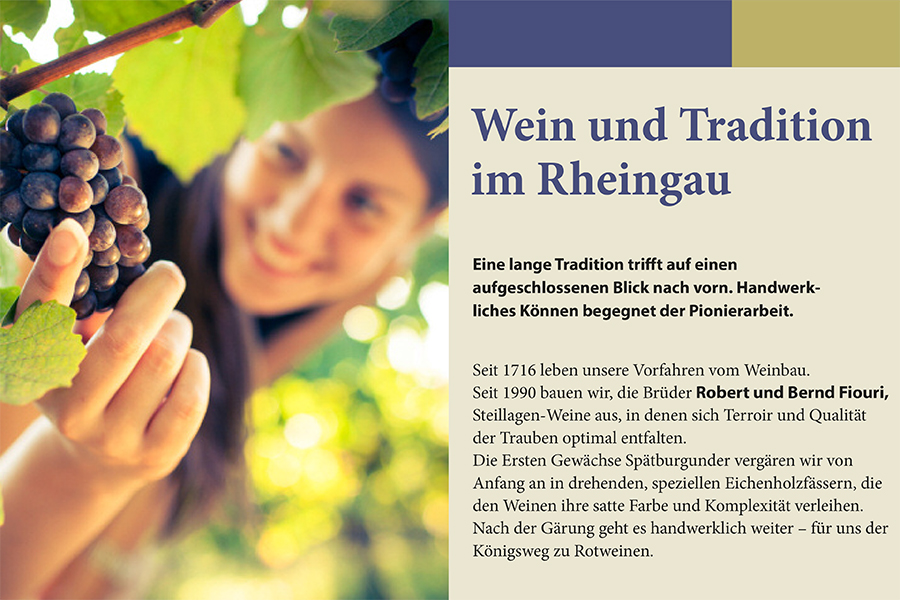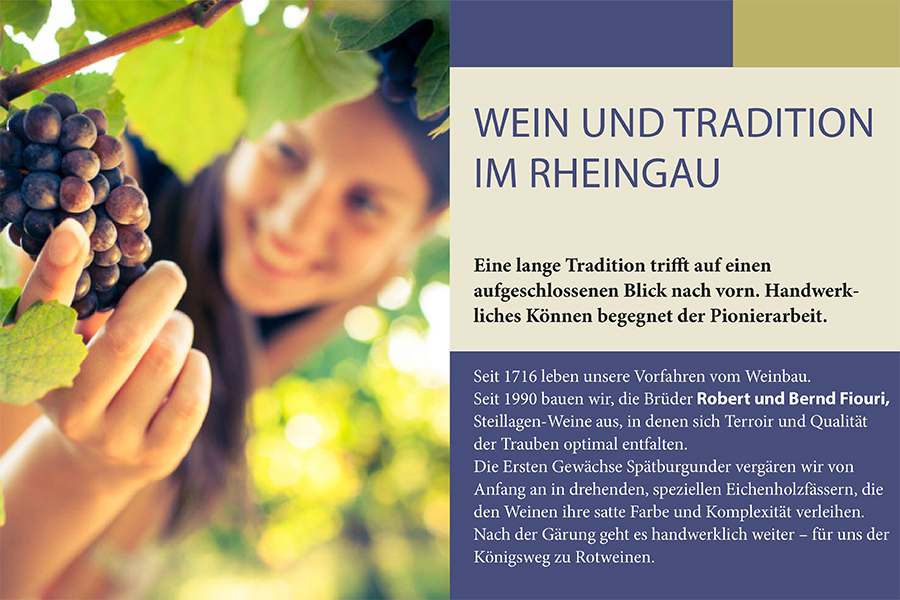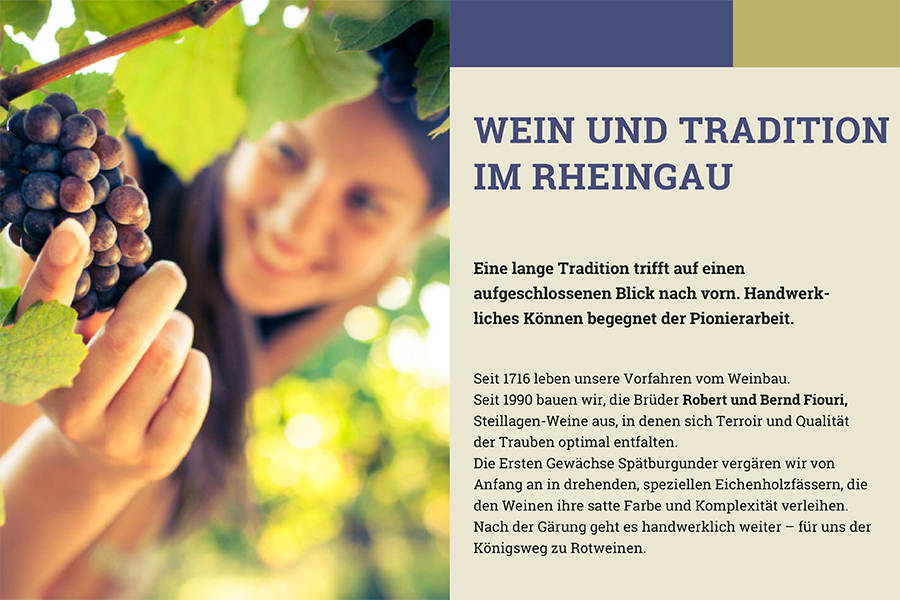
Schriften mischen und auszeichnen: So wählen Sie die richtige Schrift für ein Corporate Design
Schriftauswahl für ein Corporate Design
Beim Entwickeln eines neuen Corporate Designs (CD) steht oft die Königsdisziplin der Typografie an erster Stelle: die Auswahl der Schrift mitsamt möglichen Schriftmischungen und -auszeichnungen. Auch professionelle Designer tun sich mitunter damit schwer. Die ursprüngliche Frage bei der Auswahl von Schriften ist, ob das Produkt oder die Dienstleistung für traditionelle oder moderne Werte steht und ob zur Schriftauswahl eine Serifenschrift oder lieber eine Grotesk verwendet werden soll. Im Folgenden möchte ich dazu ein paar Praxis-Tipps geben und drei Methoden vorstellen, die ich selber häufig anwende, um schnell und sicher zu einer ansprechenden Schriftauswahl und -mischung zu kommen. Als Beispiel nehme ich dafür ein Corporate Design für ein Weingut.
Schriften finden für ein Corporate Design: Attribute sammeln im Textcluster
Der klassische Weg zur CD-Schrift führt über ein Textcluster. In diesem sammeln Sie geeignete Attribute zum Unternehmen, seinen Produkten oder Dienstleistungen, die später mit den Ausdrucksmöglichkeiten von Fonts umgesetzt werden. Mit einem Weingut verbinde ich zum Beispiel die Attribute Natur, Ökologie, Landschaft, Boden, Handarbeit, Geschmack, Lebensfreude, Genuss, Wandern etc. Danach versuchen Sie zu diesen Begriffen geeignete Fonts zu finden: Zu Natur & Ökologie würde zum Beispiel die Rockwell Bold passen, zu Lebensfreude & Genuss die Gurlz MT. Eine traditionelle Wirkung entfaltet unter anderem die Minion Pro mit der Auszeichnung in Kapitälchen. Diese Methode ist sehr zuverlässig, aber auch sehr mühselig und langwierig. Und überhaupt: Das ständige Rauf- und Runterscrollen im Schriftmenü ist keine meiner liebsten Beschäftigungen. Deshalb jetzt:
Drei alternative Methoden zur Schriftauswahl für ein neues CD
Methode 1: Die Alleskönner unter den Corporate Fonts
Wenn die Zeit drängt und mir der Kunde schon im Nacken sitzt, verwende ich bei der Gestaltung von CD-Materialien die Alleskönner und Arbeitspferde der Fonts: die Minion Pro und die Myriad Pro. Diese Fonts aus den Gruppen Serif und Non-Serif sorgen für Abwechslung im Layout und haben die bemerkenswerten Eigenschaften, dass sie zu fast jedem Corporate Design passen, sich auf fast jedem Betriebssystem befinden, untereinander gut mischbar sind und von ihrer Schriftästhetik die altgedienten Schlachtschiffe Helvetica und Times wohltuend ablösen. Sie verfügen darüber hinaus über gute Auszeichnungsformen und Open-Type-Ressourcen.
Manch einer wird jetzt einwenden, dass die Schriften aufgrund ihrer statischen und nichtstatischen Formsprache (schräges o, e bei der Minion Pro) in der Schriftmischung und Schriftauszeichnung wenig zusammenpassen. Dem möchte ich entgegnen: Typografie ist keine Formelsammlung! Also auch wenn Myriad Pro und Minion Pro nach den Regeln der Kunst nicht zusammen gehören, beweisen folgende Beispiele, dass sie sehr gut harmonieren:
ie Fonts Myriad Pro und Minion Pro als „schnelle Anwendung“ von Schriftmischung und Schriftauszeichnung im Corporate Design eines Weinguts.
Beispiel oben Die Fonts Myriad Pro und Minion Pro als „schnelle Anwendung“ im agilen Projektmanagement zur Schriftmischung und Schriftauszeichnung im Corporate Design eines Weinguts. In der Regel tausche ich die Schriften später aus, wenn in der CD-Entwicklung „Land in Sicht“ ist. Bis dahin sind sie die perfekten Begleiter, um effizient voran zu kommen.
ie Fonts Myriad Pro und Minion Pro als „schnelle Anwendung“ von Schriftmischung und Schriftauszeichnung im Corporate Design eines Weinguts.
Beispiel oben Dieselben Fonts in umgekehrter Anwendung: Für die Titelschrift habe ich die Myriad Pro in der Auszeichnung Versal verwendet. Obwohl es sich bei beiden Beispielen um die gleichen Fonts handelt, wirken die Erscheinungsbilder grundverschieden.
Methode 2: Die Zeitgemäßen unter den Corporate Fonts
Man muss nicht auf jeden Zug aufspringen, aber manchmal bewährt es sich, aktuellen Design-Trends zu folgen. In den letzten Jahren haben aus der Schriftgruppe Serif die sogenannten Slab-Fonts die Corporate Designs erobert. Sie zieren heute namhafte Fußballvereine und Automobilclubs, Müsli-Riegel, Outdoor-Hersteller, Investment-Broker, Bio-Bauern und Präsidenten-Tower – und bringen dabei deutlich und kraftvoll die unternehmerischen Attribute zum Ausdruck.
Dabei sind die Slab-Fonts eigentlich uralte Typen. In der Schriftklassifikation nach DIN 16518 gehören sie zur Gruppe 5 der Serifenbetonten Linear-Antiqua, auch Egyptienne genannt. Ihren Ursprung finden sie in den USA in der Mitte des 19. Jahrhunderts. Sie sind uns aus spannenden und weniger spannenden Wild-West-Filmen bekannt („Kitty’s Saloon“ und ähnliche Aufschriften). Durch das wachsende Konsumverhalten in der Zeit der Industriellen Revolution nahm der Bedarf an Werbeblättern und Anzeigen in den Tageszeitungen massiv zu. Damit einer den anderen mit seinen Werbebotschaften übertrumpfen konnte, etablierten sich die Schriften mit den „dicken Füssen“, den Slabs.
Slab-Schriften im Corporate Design liegen im Trend
Beispiel oben Die Roboto Slab als Schriftfamilie in Titelsatz und Lesetext. Nicht nur zur Schriftmischung innerhalb eines Corporate Designs sondern auch zur Auszeichnung von Schriften innerhalb von Textblöcken sind Schriftfamilien ein sicherer Weg, um ästhetische Fehlgriffe zu vermeiden.
Methode 3: Die Praktischen unter den Corporate Fonts
Wem die ersten beiden Methoden der Schriftmischung zu simpel oder zu wenig kreativ erscheinen, der kann zur Typo-Methode „praktisch“ übergehen: den Schriftsippen oder auch heute Superfamilies genannt. Diesen Begriff können die wenigsten Gestalter wirklich erklären. Dabei haben sie Schriftsippen oder Superfamilies vielleicht schon häufiger verwendet als es Ihnen bewusst ist. Schriftsippen sind Hybrid-Schriften mit den Merkmalen aus verschiedenen Gruppen, die aber einen gleichen Charakter haben. Eine der meistbenutzen Schriftsippen ist die altbekannte Schrift Rotis des Ulmer Typografen Otl Aicher. Neben der ursprünglichen Form der serifenlosen Linear-Antiqua gibt es dieselbe Schrift noch mit Halbserifen und Serifen – und das in den verschiedenen Auszeichnungen Regular, Bold, Italic und so weiter.